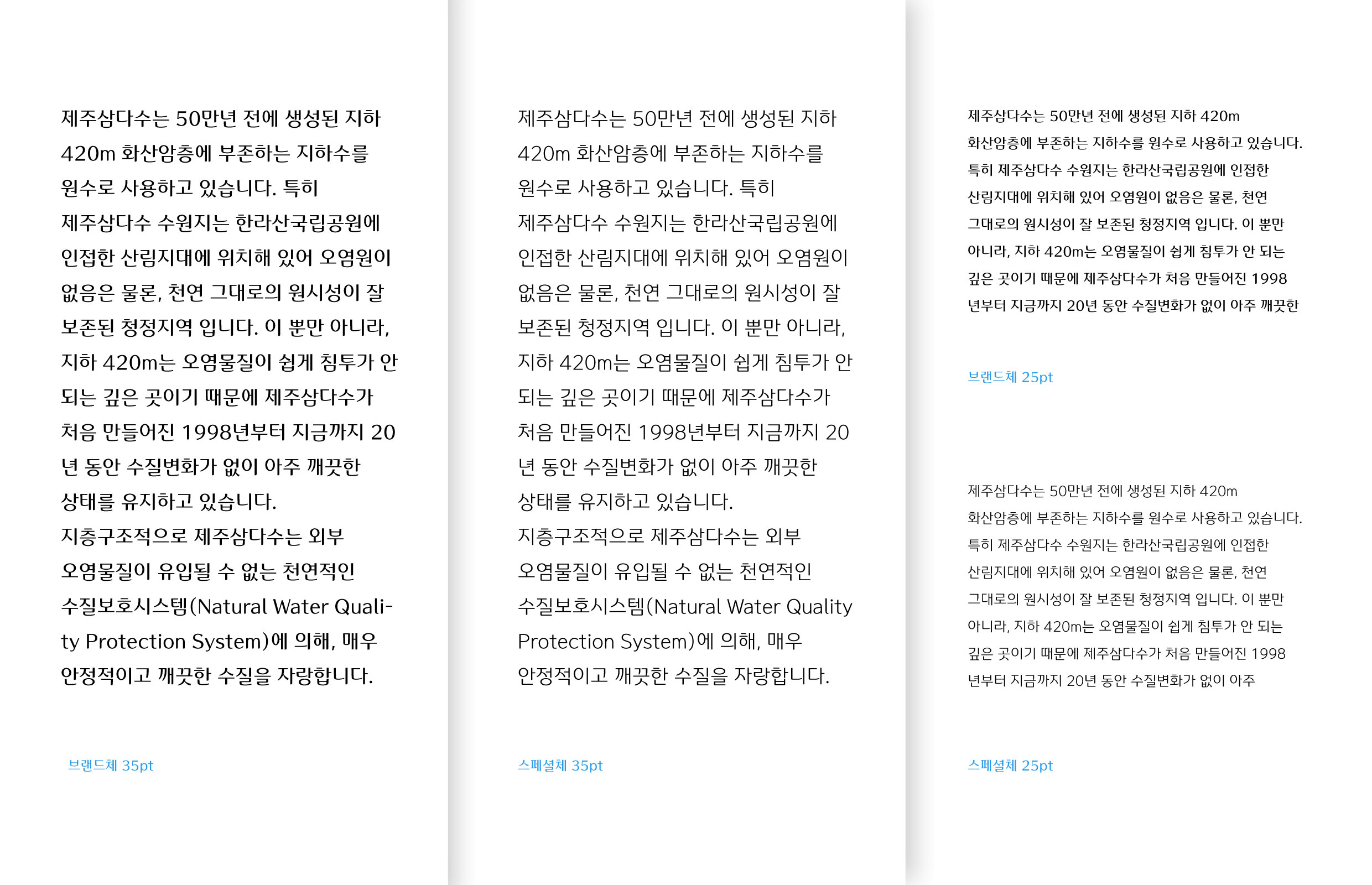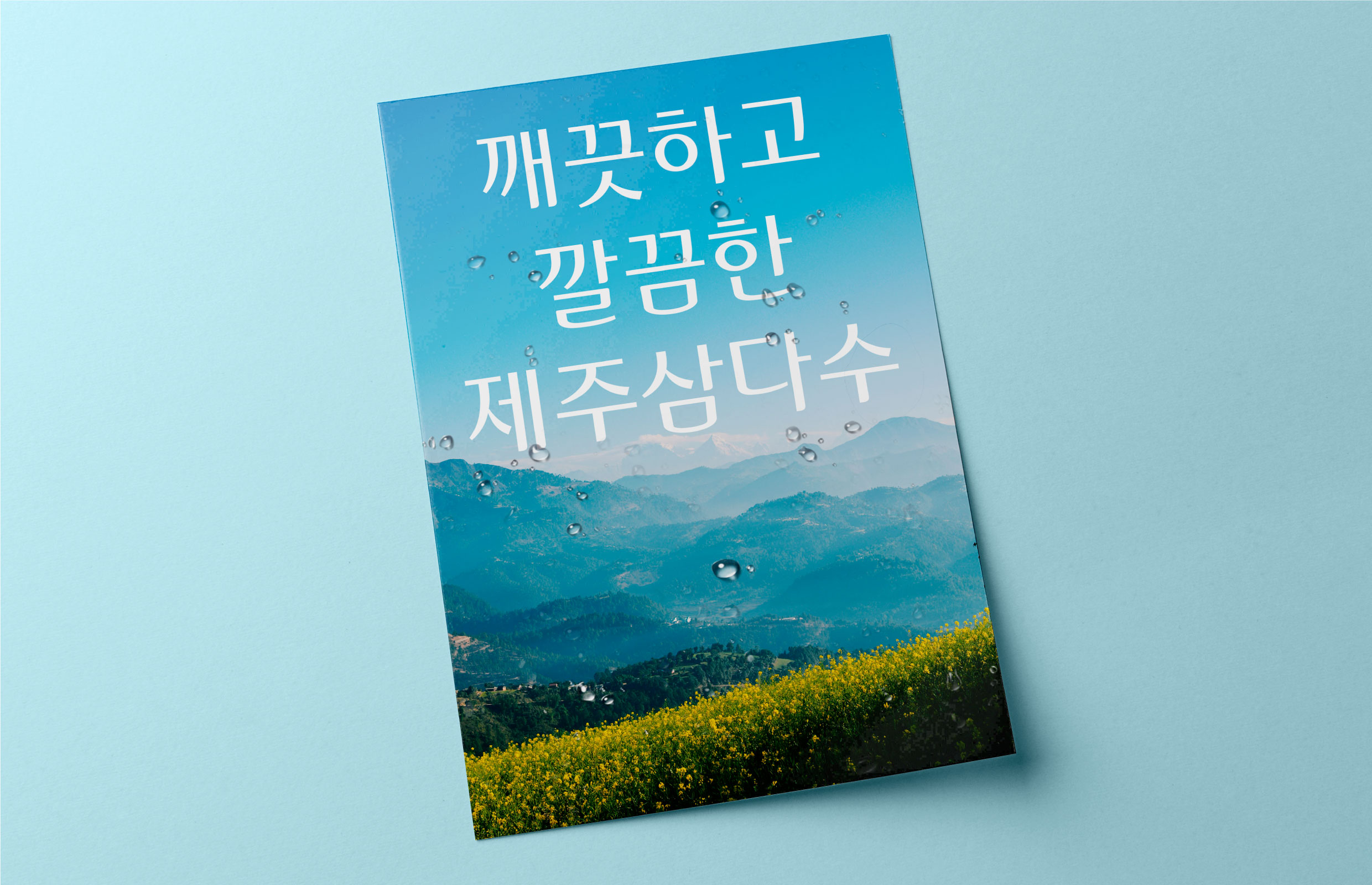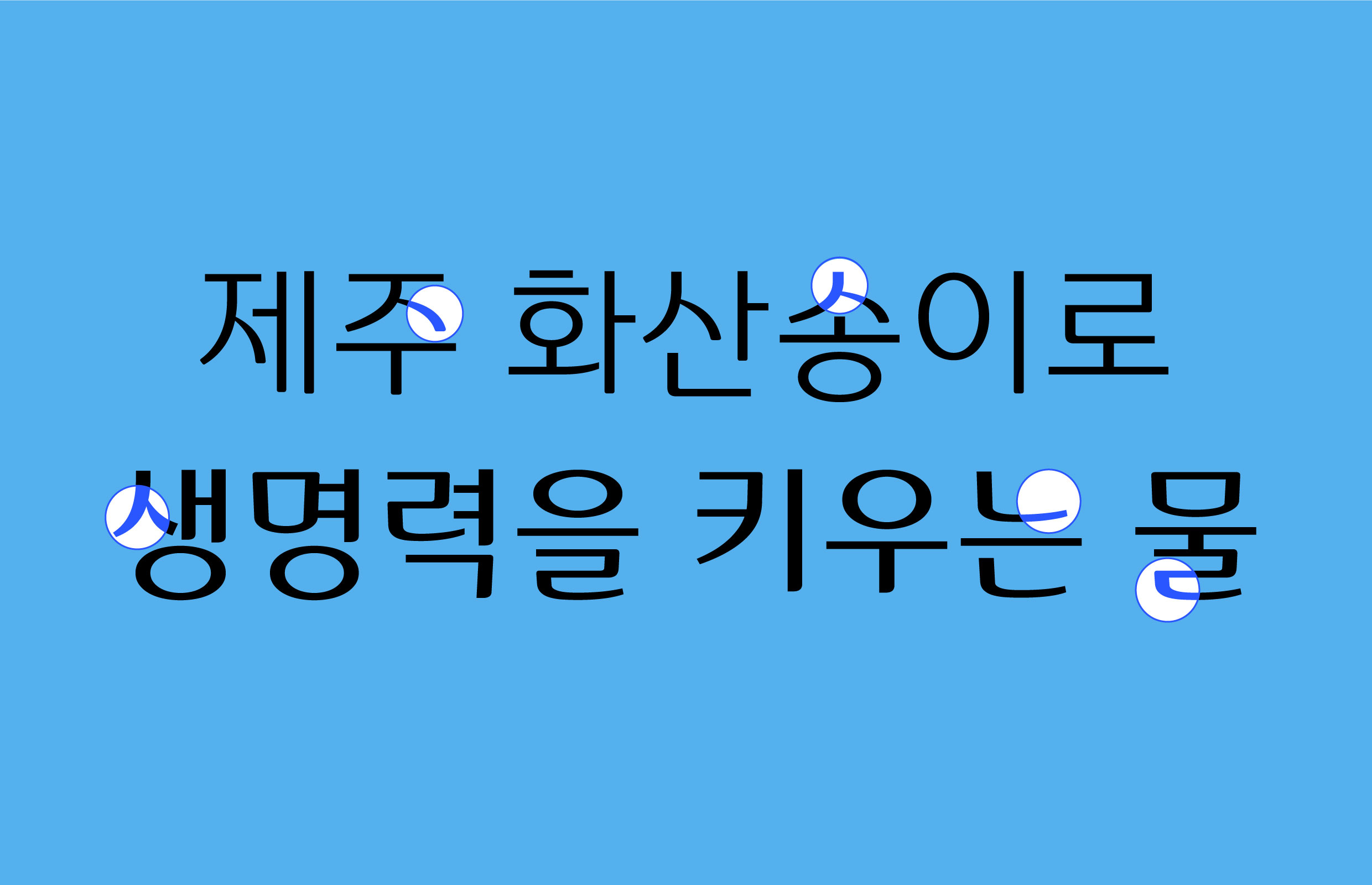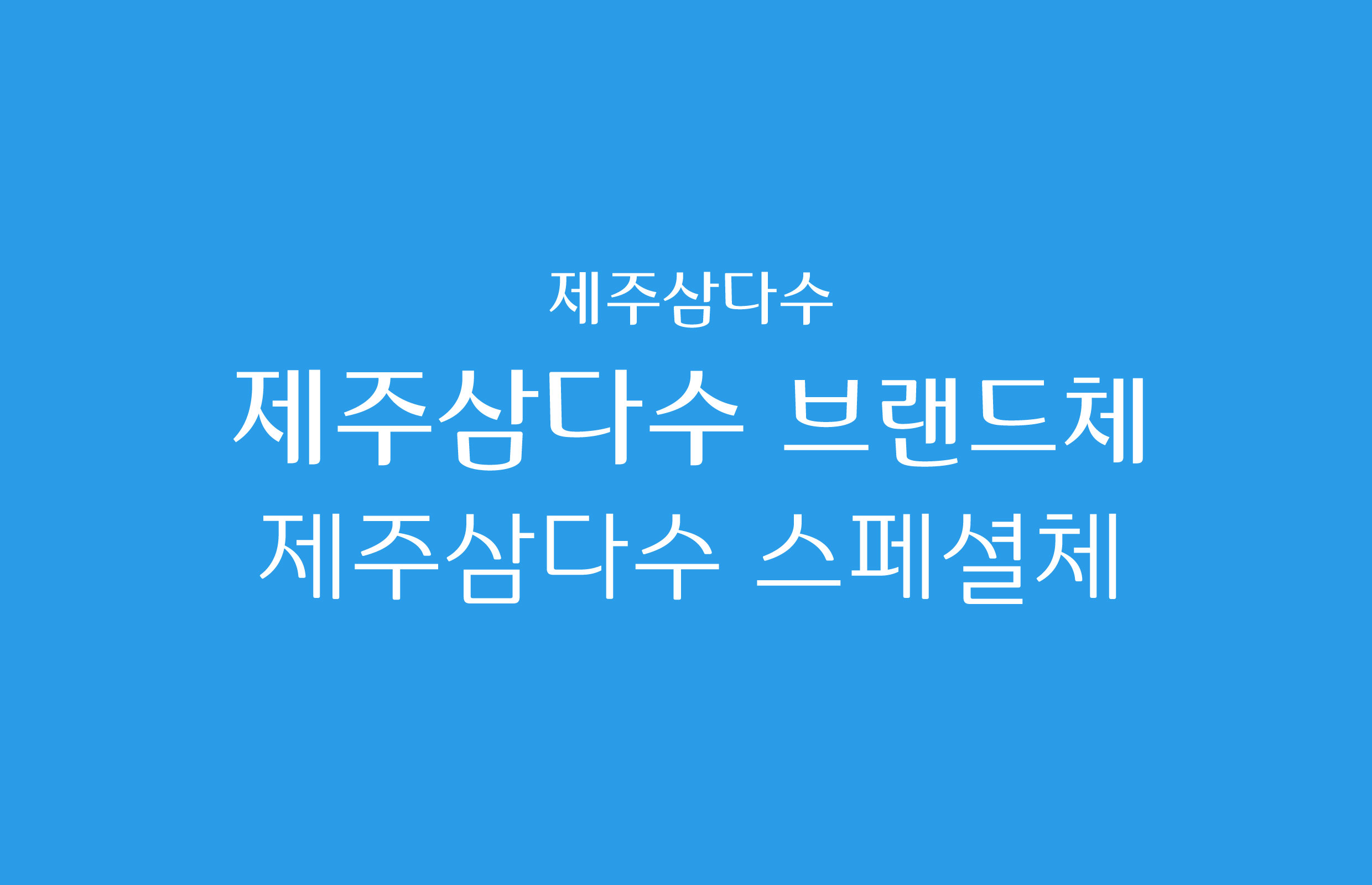
제주개발공사 [제주삼다수]
2020이후
제주개발공사 [제주삼다수]
제목용 서체인 ‘브랜드체’와 본문용 서체인 ‘스페셜체’로 이루어진 서체. 제주삼다수 로고의 특징과 청정 제주의 맑고 깨끗한 삼다수를 담은 컵의 형태를 디자인 요소로 적용하였다. 물과 물컵을 연상시키는 유려한 곡선미가 특징이다.